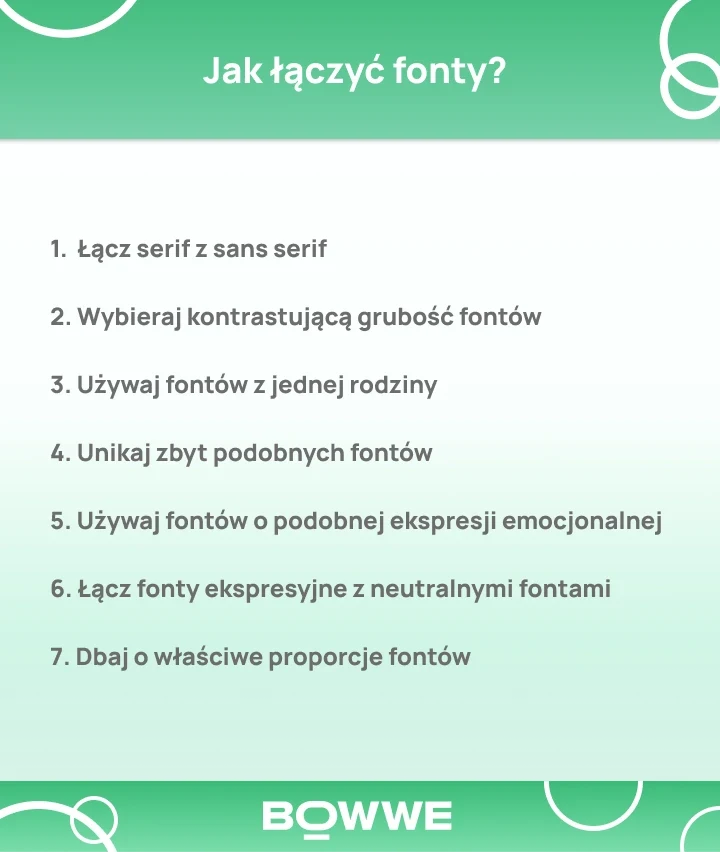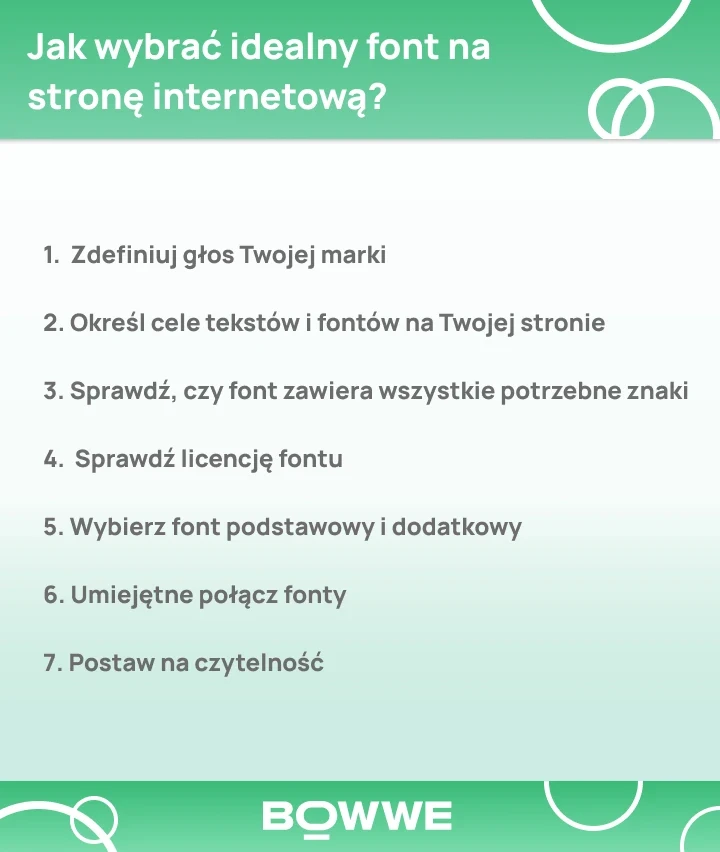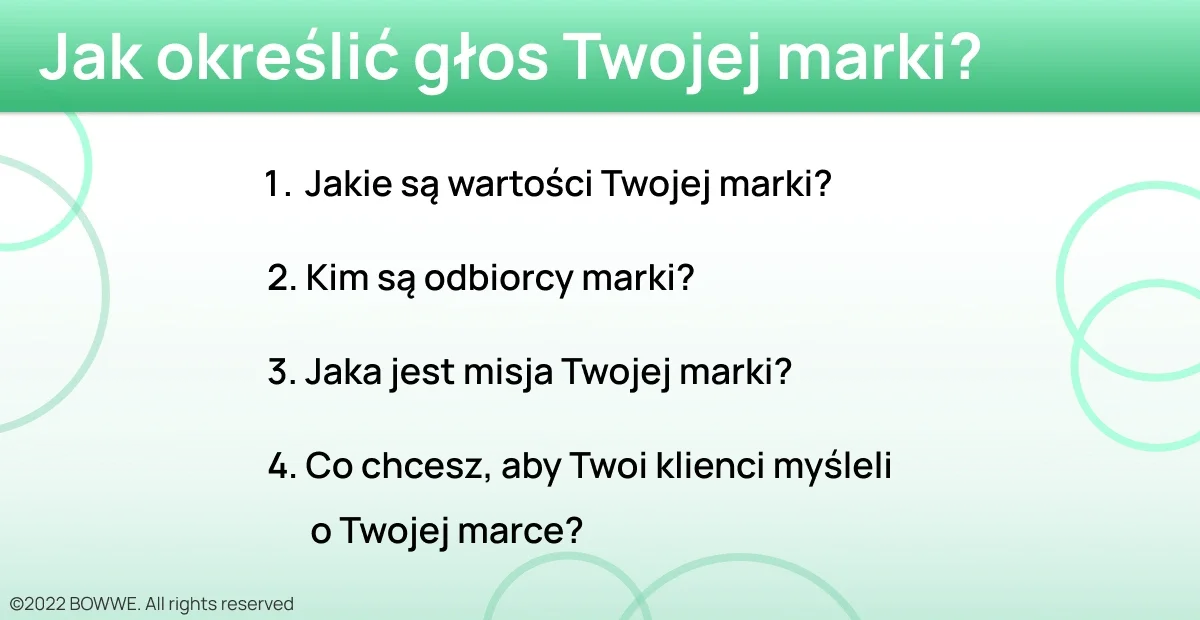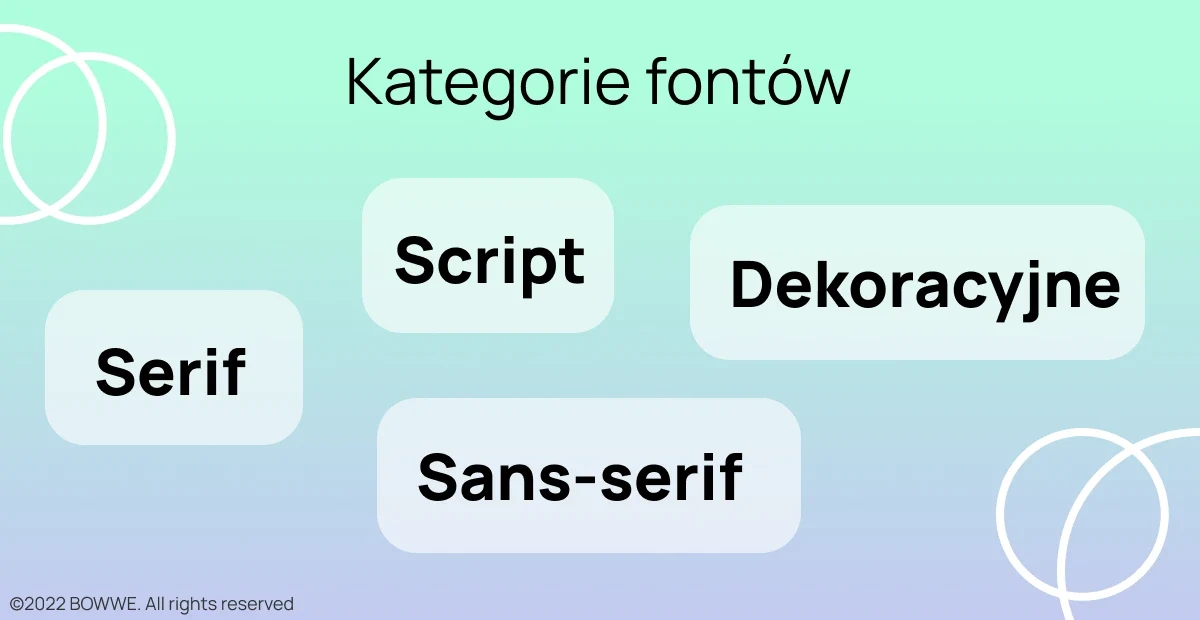
Odświeżasz lub tworzysz stronę internetową od podstaw? Teraz nadszedł czas, aby wybrać najlepszy font. To kluczowy wybór. Czemu? Układ i wygląd tekstów znacząco wpływa na estetykę, funkcjonalność i czytelność Twojej strony. Strona z dobrymi fontami jest dużo bardziej przyjazna dla użytkownika i przekłada się na wyższą konwersję!
Wybór najlepszego fontu dla strony internetowej nie jest łatwy. Jednak wszystko, co musisz zrobić, to postępować zgodnie z tym przewodnikiem, aby upewnić się, że wybierzesz najlepszy font który dopełni Twoją stronę!
Jak wybrać najlepszy font do wykorzystania na stronie?
Oto 7 kluczowych kroków, które powinieneś przejść:
1. Zdefiniuj głos Twojej marki
2. Określ cele tekstów i fontów na Twojej stronie
3. Sprawdź, czy font zawiera wszystkie potrzebne znaki
4. Sprawdź licencję fontu
5. Wybierz font podstawowy i dodatkowy
6. Umiejętne połącz fonty
7. Postaw na czytelność
Przyjrzyjmy się, jak wykonać każdy tych kroków w praktyce.
Krok I: Zdefiniuj głos Twojej marki
Jeśli chodzi o wybór fontów, Twoja marka jest najważniejsza - to, co klienci wiedzą i myślą o Twojej firmie. Dlatego tak ważne jest, aby wybrać odpowiedni font dla Twojej firmy. Ale jak określasz głos swojej marki? I jak wybrać fonty, które będę go odzwierciedlać?
Aby określić charakter Twojej marki, musisz zadać sobie kilka pytań:
1. Jakie są wartości Twojej marki?
2. Kim są odbiorcy marki?
3. Jaka jest misja Twojej marki?
4. Co chcesz, aby Twoi klienci myśleli o Twojej marki?
Zapisz odpowiedzi na te pytania! Pomogą Ci w kolejnych krokach w doborze fontu, które wskażę w tym artykule!
Krok II: Zdefiniuj cele tekstów i fontów na Twojej stronie
W kwestii projektowania strony internetowej, cel tekstu i fontu, który wybierzesz, są ważne. Pomagają nadać ton i przekazać wiadomość odwiedzającym. Więc jakie są cele twojego tekstu i fontu?
Tekst na Twojej stronie powinien być czytelny i wystarczająco duży, aby można go było szybko zobaczyć. Powinieneś także wiedzieć, jak ważna będzie rola tekstu.
W niektórych serwisach tekst nie odgrywa znaczącej roli. Służy na przykład do tworzenia krótkich opisów, więc font może być w tym przypadku bardziej dekoracyjny. Z drugiej strony ci, którzy przekazują większość informacji za pomocą tekstu (np. na blogu), muszą przede wszystkim skoncentrować się na tym, aby używany font był czytelny i nie męczyło oczu.
Wybrany font powinien współgrać z zawartością Twojej witryny. Na przykład, jeśli prowadzisz witrynę firmową, możesz użyć czcionki szeryfowej, aby tekst wyglądał bardziej profesjonalnie. I odwrotnie, jeśli prowadzisz stronę internetową o bardziej swobodnym tonie, możesz użyć czcionki bezszeryfowej.
Kategorie fontów
Fonty dzielą się głównie na:
1. szeryfowe
2. bezszeryfowe
3. skryptowe
4. dekoracyjne lub displayowe
Fonty szeryfowe
Mają poprzeczne lub ukośne zakończenia linii (tzw. szeryfowe). Zastosowanie szeryfów nadaje tekstom tradycyjny, bardziej elegancki charakter. Fonty te od dawna są używane w publikacjach papierowych (głównie w książkach), ponieważ szeryfy pomagają czytelnikom śledzić linię tekstu, ułatwiając w ten sposób czytanie.
Czcionki szeryfowe ze względu na swój dekoracyjny charakter również dobrze prezentują się na stronach internetowych... ale przede wszystkim, gdy są wykorzystywane jako dodatkowe elementy treści, np.:
1. nagłówki,
2. cytaty,
3. podtytuły,
4. logotypy,
5. slogany.
Mogą być stosowane przez firmy, które chcą podkreślić swoje wieloletnie doświadczenie, przywiązanie do tradycji i stabilność.
Popularne fonty szeryfowe: Times New Roman, Georgia, Palatino, Bookman Old Style, Garamond, Courier, Lucida, Century, Arno Pro, MS Serif.
Fonty bezszeryfowe
Fonty bezszeryfowe są pozbawione szeryfów. Z tego powodu mają bardziej nowoczesny i minimalistyczny charakter.
Ich użycie w Internecie stało się powszechne, ponieważ w przeszłości ekrany nie mogły poprawnie wyświetlać fontów szeryfowych. Istotnym elementem jest też to, że fonty bezszeryfowe wyświetlane na ekranie nie męczą oczu.
Powinny z nich korzystać firmy, które są innowacyjne lub chcą być postrzegane jako nowoczesne i dynamiczne. Fonty te cechują się dostępnośnią i prostotą, dzięki czemu będą dobrym wyborem dla firmy, która kieruje swoje usługi do młodego pokolenia.
Popularne fonty bezszeryfowe: Arial, Open Sans, Montserrat, Helvetica, Futura, Verdana, Trebuchet MS, Universe.
Fonty skryptowe
Są to fonty naśladujące pismo odręczne. Są eleganckie i formalne, ale też trochę humorystyczne. Wśród nich można znaleźć zarówno bardzo ozdobne, jak i dość proste fonty.
Ich zaletą jest duża wyrazistość. Niosą ogromny ładunek emocjonalny, którym można wywołać u odbiorców określoną reakcję. Poza tym fonty skryptowe przyciągają uwagę i pozwalają na komunikowanie poważnych lub humorystycznych treści (w zależności od rodzaju fontu).
Eleganckie fonty skryptowe są idealne na zaproszenia ślubne i kartki okolicznościowe. Na stronach internetowych sprawdzą się, gdy użyjesz ich do pisania mniejszych elementów tekstowych - np. nagłówków czy cytatów.